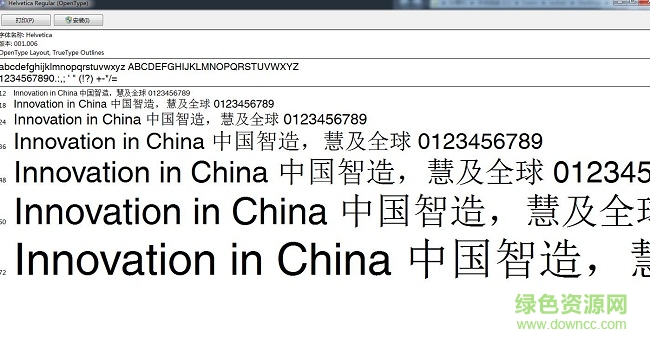
helvetica regular是什么字體?helvetica regular字體是一款蘋(píng)果電腦的默認(rèn)字體,屬于無(wú)襯線(xiàn)字體類(lèi),風(fēng)格簡(jiǎn)潔,粗細(xì)勻稱(chēng),適合商業(yè)設(shè)計(jì),歡迎下載!
Helvetica出自瑞士字體設(shè)計(jì)師Eduard Hoffmannh和Max Miedinger之手,體現(xiàn)了瑞士設(shè)計(jì)的理性主義精神,同時(shí)被認(rèn)為是現(xiàn)代主義設(shè)計(jì)理念的典范。
被大量使用于企業(yè)Logo上, 如3M、美國(guó)航空、BMW、德國(guó)漢莎航空公司、Fendi、Jeep、英特爾、無(wú)印良品、雀巢、松下、Microsoft、三菱電機(jī)、摩托羅拉、豐田、三星、渣打銀行等。